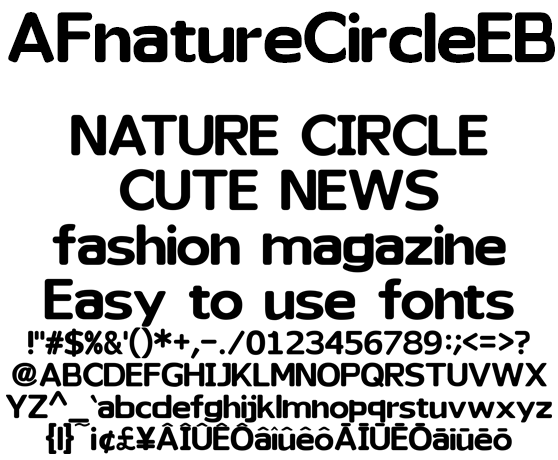
丸くてキュートな極太欧文フォント AFnatureCircleEB
AFnatureCircleEB
極太丸ゴシックな欧文フォントは、キャッチな場面の同人系、コミック、アニメ、ゲームに最適。パンフレット、リーフレット、フライヤー、ファッション系コンテンツに使えるフォントです。日本のローマ字表記で使われる訓令式やヘボン式で扱う Ô や Ō を収録、人名地名へのアプローチもリアルです。